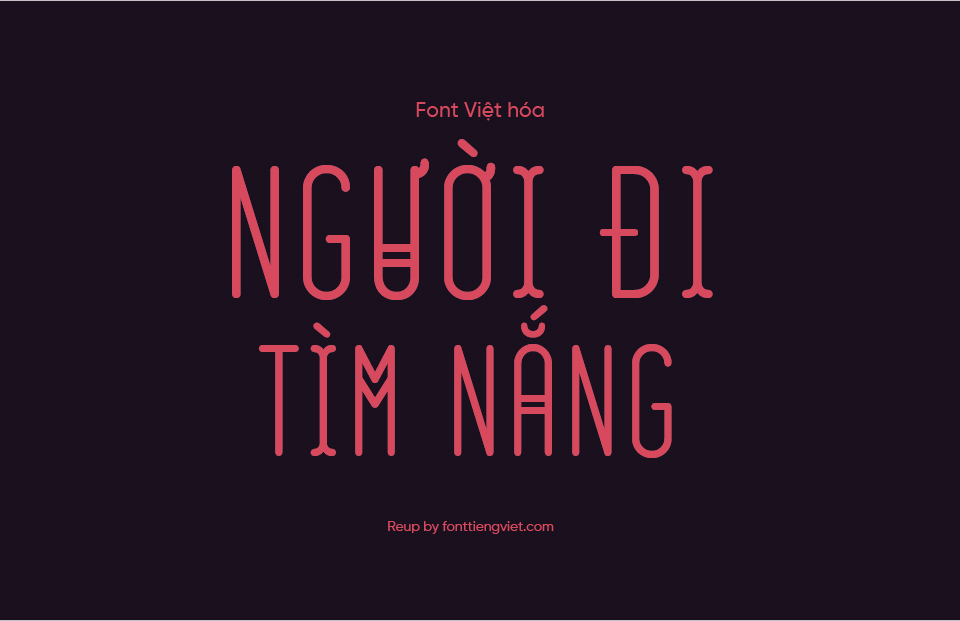
Font Việt hóa MTD Gogoia Deco – Tuyệt Chiêu Thiết Kế Ấn Tượng cho Học Sinh
Trong thế giới thiết kế đồ họa, việc lựa chọn một Font Chữ phù hợp có thể quyết định 50% sự thành công của một ấn phẩm. Đặc biệt đối với học sinh, sinh viên, những người thường xuyên phải làm slide thuyết trình, poster dự án hay kỷ yếu tốt nghiệp, nhu cầu về một phông chữ vừa đẹp, vừa độc đáo lại phải hỗ trợ đầy đủ tiếng Việt là vô cùng cấp thiết. Hôm nay, chúng ta sẽ đi sâu vào một tuyệt phẩm đang được cộng đồng thiết kế trẻ săn đón: Font Việt hóa MTD Gogoia Deco. Đây không chỉ là một phông chữ, mà là công cụ giúp các ý tưởng sáng tạo của bạn bừng sáng, làm nổi bật mọi dự án học đường hay các chiến dịch truyền thông của trường.
Sự kết hợp giữa phong cách Art Deco cổ điển cùng nét hiện đại, vui tươi khiến bộ font này trở thành lựa chọn hàng đầu cho các thiết kế cần sự thu hút và tính nghệ thuật cao. Nếu bạn đang tìm kiếm một “vũ khí bí mật” để nâng cao điểm số đồ họa hoặc gây ấn tượng mạnh mẽ trong kỳ thi tốt nghiệp sắp tới, việc tìm hiểu sâu về Font Việt hóa MTD Gogoia Deco là điều không thể bỏ qua.
Khám Phá Vẻ Đẹp Đặc Trưng của Font Việt hóa MTD Gogoia Deco
MTD Gogoia Deco nổi bật với các đường nét hình học sắc sảo nhưng vẫn giữ được sự mềm mại, lôi cuốn. Phông chữ này mang hơi hướng của thập niên 1920-1930, thời kỳ hoàng kim của nghệ thuật trang trí (Deco), mang lại cảm giác sang trọng nhưng không hề cứng nhắc. Chính sự linh hoạt trong thiết kế này giúp nó phù hợp với nhiều loại hình nội dung khác nhau, từ tiêu đề ấn phẩm, logo cho đến các đoạn văn ngắn trong các dự án sáng tạo.
Đối với học sinh, sinh viên, Gogoia Deco là giải pháp tuyệt vời cho các dự án đòi hỏi tính thẩm mỹ cao như: thiết kế bìa sách, minh họa báo tường, làm các infographic phức tạp hoặc tạo nên những tấm thiệp chúc mừng độc đáo trong các dịp lễ. Sự rõ ràng và khả năng đọc tốt (readability) của nó cũng đảm bảo thông điệp luôn được truyền tải một cách hiệu quả nhất, ngay cả khi sử dụng ở kích thước nhỏ.
Font Việt hóa MTD Gogoia Deco và Tầm Quan Trọng của Localization
Trong quá trình thiết kế với các font chữ quốc tế, vấn đề lớn nhất mà người dùng Việt Nam thường gặp phải chính là lỗi hiển thị dấu. Khoảng cách giữa các ký tự (kerning), vị trí đặt dấu (diacritics) không chuẩn sẽ làm hỏng bố cục tổng thể. Đây là lý do tại sao phiên bản Font Việt hóa MTD Gogoia Deco lại trở nên quan trọng đến vậy.
- Đảm bảo tính thẩm mỹ: Phiên bản Việt hóa đã được tối ưu hóa để các dấu tiếng Việt (sắc, huyền, hỏi, ngã, nặng, mũ) hiển thị hài hòa, không bị chồng chéo lên nhau hay phá vỡ nhịp điệu của chữ.
- Tăng tính chuyên nghiệp: Các bài luận, báo cáo hoặc slide thuyết trình sử dụng font chuẩn dấu sẽ được đánh giá cao hơn về mặt hình thức.
- Dễ dàng sử dụng: Người dùng không cần phải tùy chỉnh thủ công hay lo lắng về các lỗi hiển thị phổ biến khi chuyển đổi giữa các phần mềm thiết kế khác nhau.
Ứng Dụng Sáng Tạo: MTD Gogoia Deco Trong Các Dự Án Học Đường
Nền tảng giáo dục ngày càng khuyến khích sự sáng tạo cá nhân, đặc biệt qua các dự án thực hành. Font Việt hóa MTD Gogoia Deco chính là yếu tố then chốt giúp học sinh tạo ra những sản phẩm nổi bật, vượt trội so với các thiết kế sử dụng font mặc định nhàm chán như Times New Roman hay Arial.
Thiết kế Kỷ Yếu Tốt Nghiệp Gây Ấn Tượng
Kỷ yếu là nơi lưu giữ những khoảnh khắc đẹp nhất của tuổi học trò. Sử dụng MTD Gogoia Deco cho các tiêu đề lớn, tên chương hoặc phần trích dẫn sẽ mang lại cảm giác hoài niệm, nghệ thuật và rất riêng biệt. Nét chữ trang trí này làm tăng tính độc đáo và giá trị lưu giữ của cuốn kỷ yếu, khiến nó trở thành món quà ý nghĩa trong mùa tốt nghiệp.
Sử Dụng Trong Bài Thi Thuyết Trình Lớn
Trong các kỳ thi cuối cấp hoặc các buổi bảo vệ đồ án, slide thuyết trình cần phải chuyên nghiệp nhưng vẫn phải hấp dẫn. MTD Gogoia Deco, khi được dùng một cách tiết chế cho các điểm nhấn quan trọng, sẽ giúp thu hút sự chú ý của giáo viên và hội đồng giám khảo. Hãy nhớ rằng, trong thiết kế, ít hơn là nhiều hơn (less is more); chỉ nên sử dụng font trang trí này cho tiêu đề và các thông điệp quan trọng nhất.
Sự lựa chọn font chữ phản ánh gu thẩm mỹ và mức độ đầu tư của người làm nội dung. Với MTD Gogoia Deco, bạn không chỉ tạo ra một sản phẩm đẹp mắt, mà còn thể hiện được sự tinh tế và chuyên nghiệp của mình trong lĩnh vực thiết kế đồ họa cơ bản.
Tóm lại, Font Việt hóa MTD Gogoia Deco là một tài nguyên quý giá, đặc biệt là với giới trẻ, học sinh và những nhà thiết kế đang tìm kiếm sự phá cách. Việc sở hữu và sử dụng phông chữ này sẽ nâng tầm chất lượng các sản phẩm đồ họa, từ đó đạt được kết quả cao trong các dự án học thuật hoặc kỳ thi tốt nghiệp. Đừng ngần ngại khám phá sức mạnh của Font Chữ nghệ thuật này ngay hôm nay để biến những ý tưởng táo bạo thành hiện thực đầy ấn tượng.